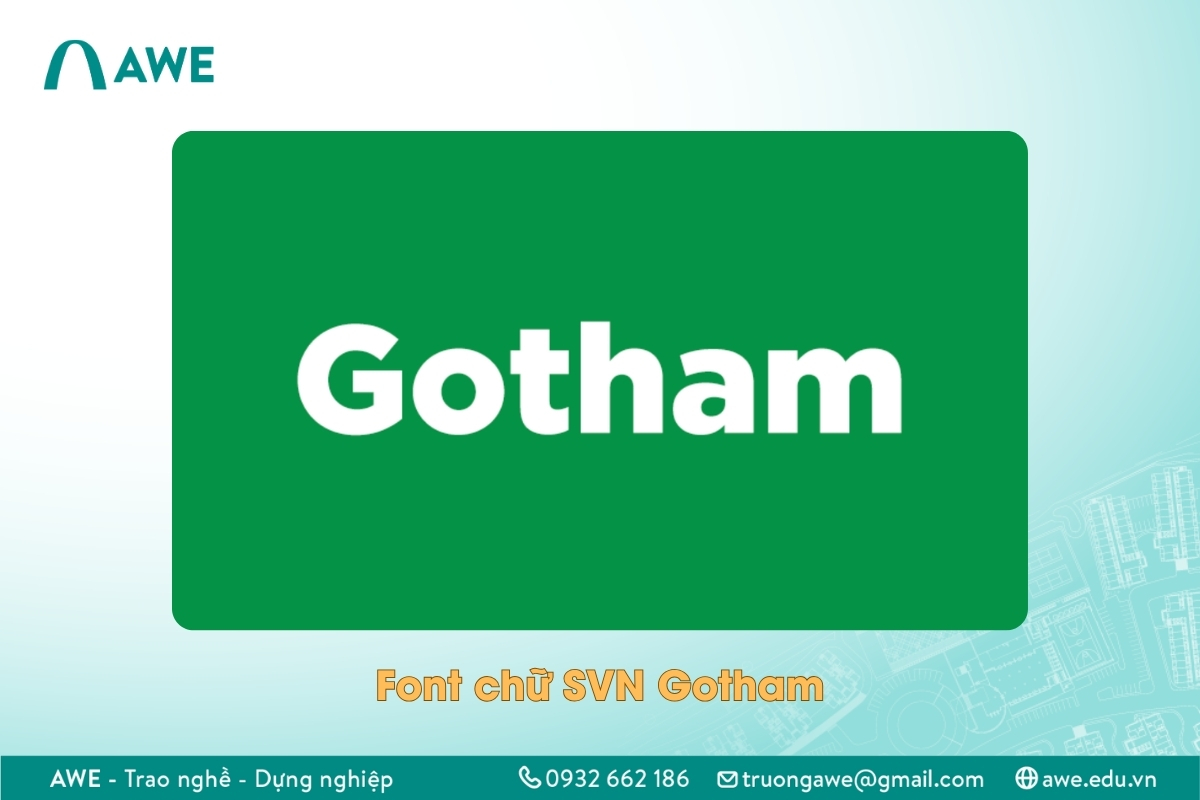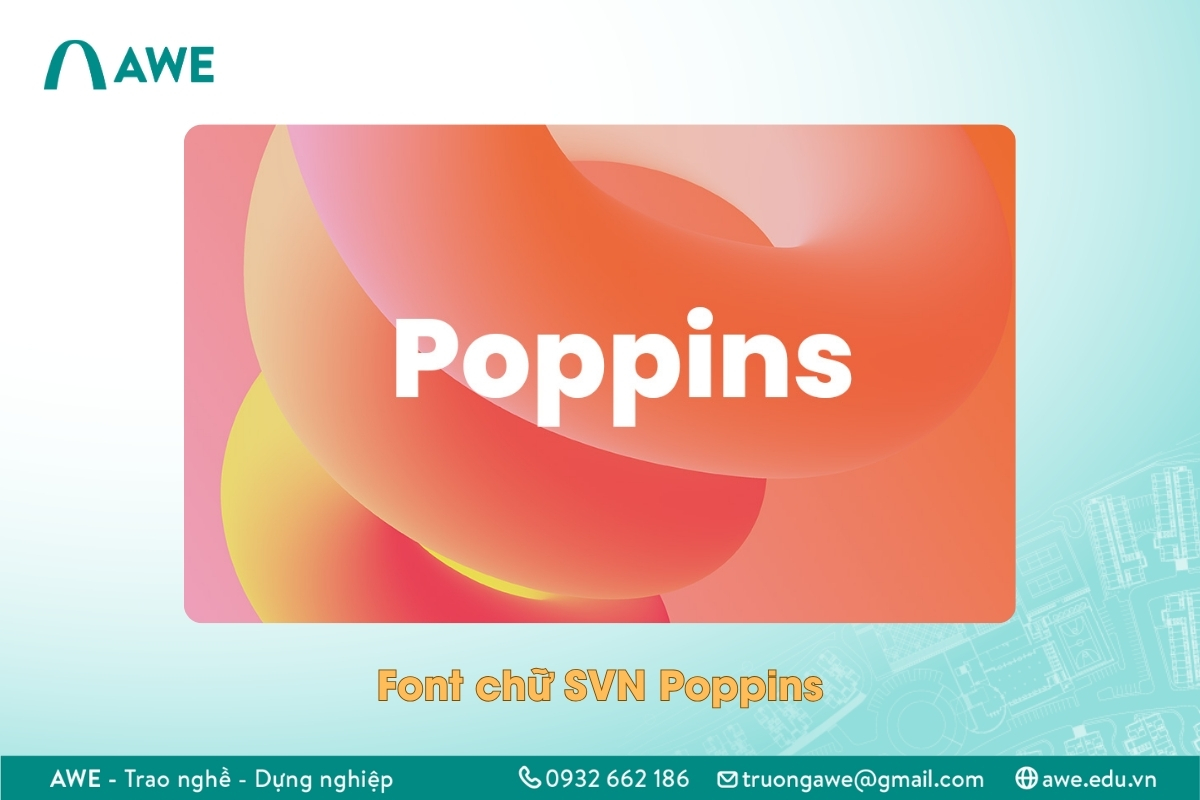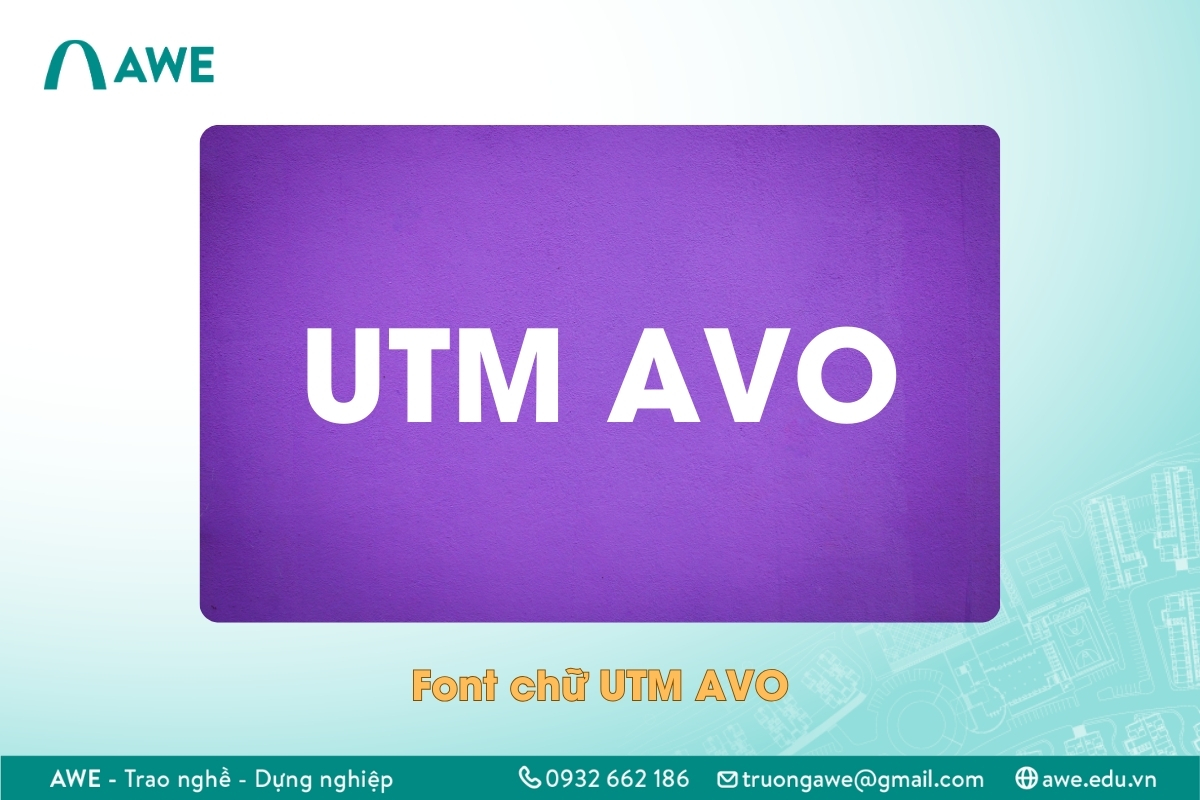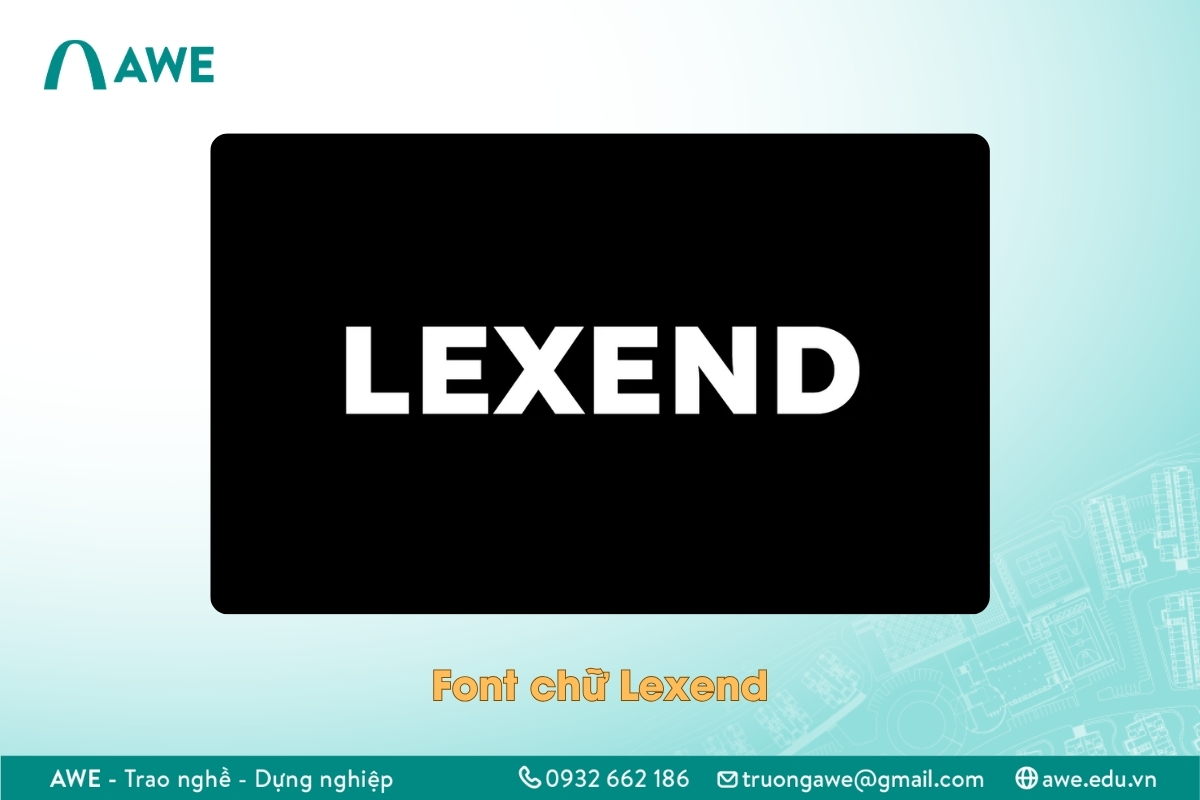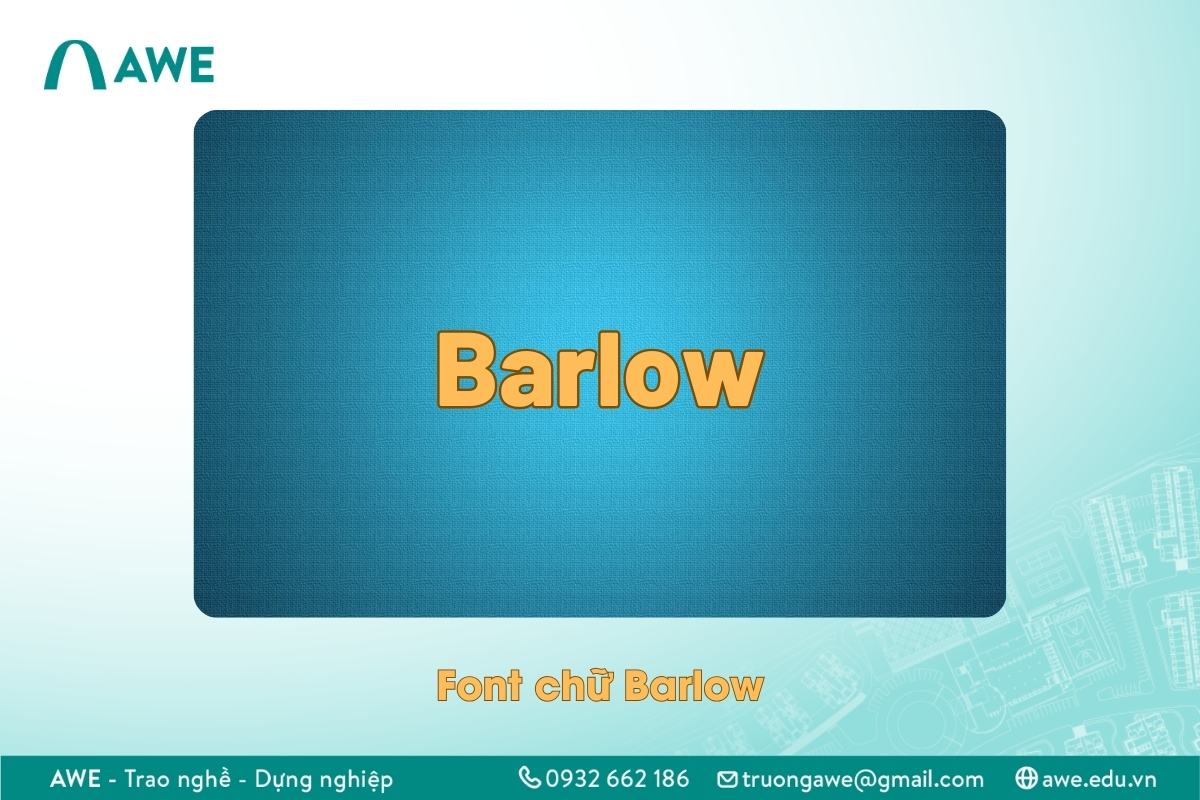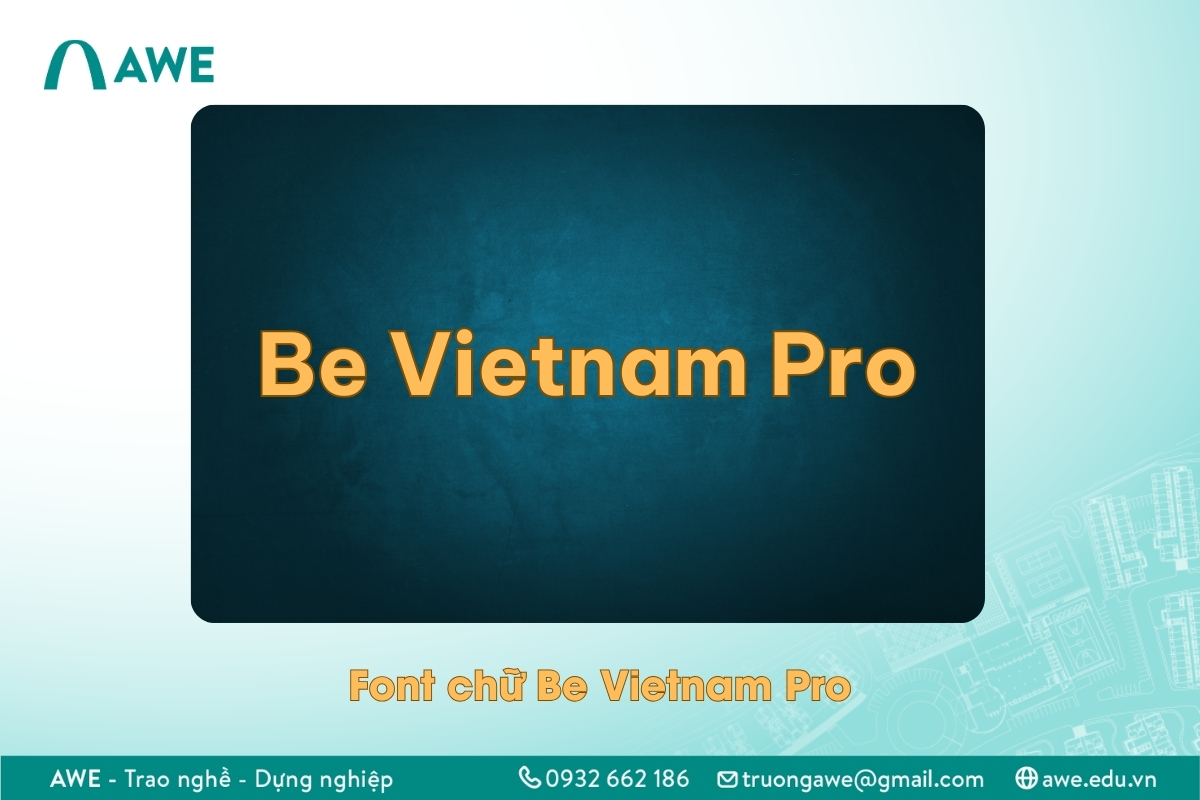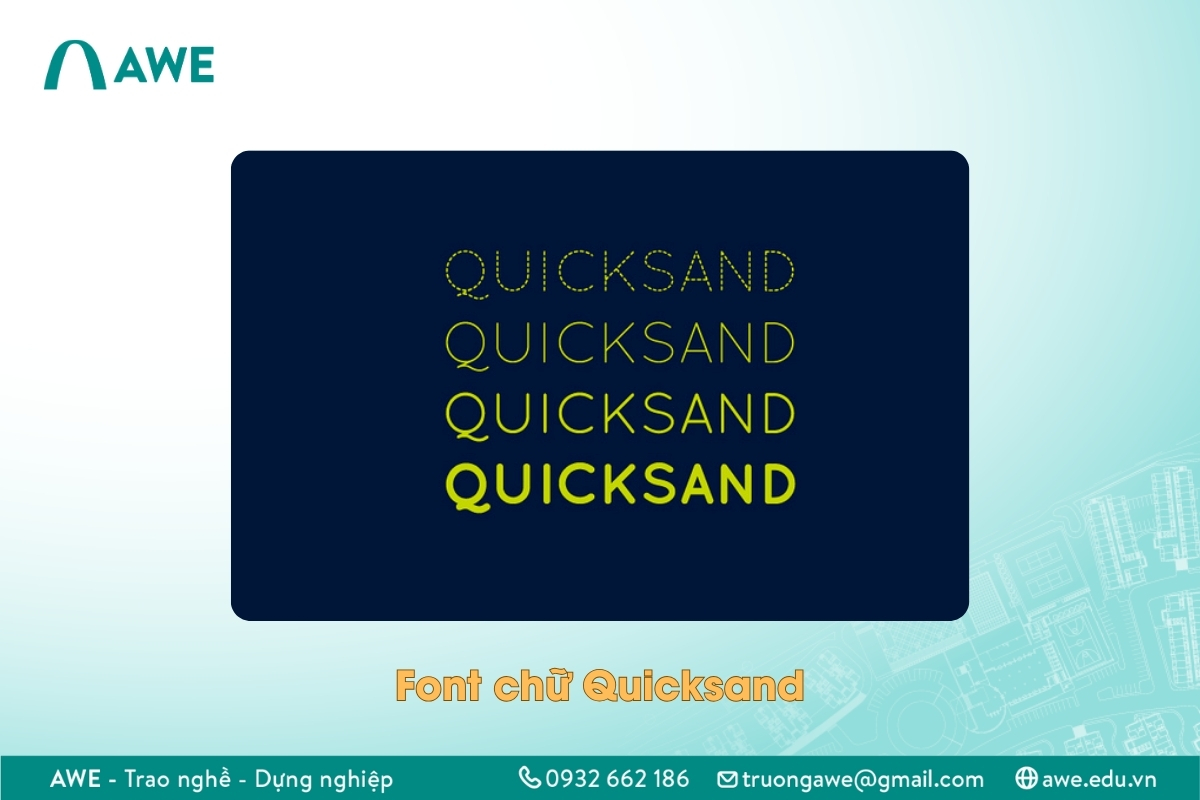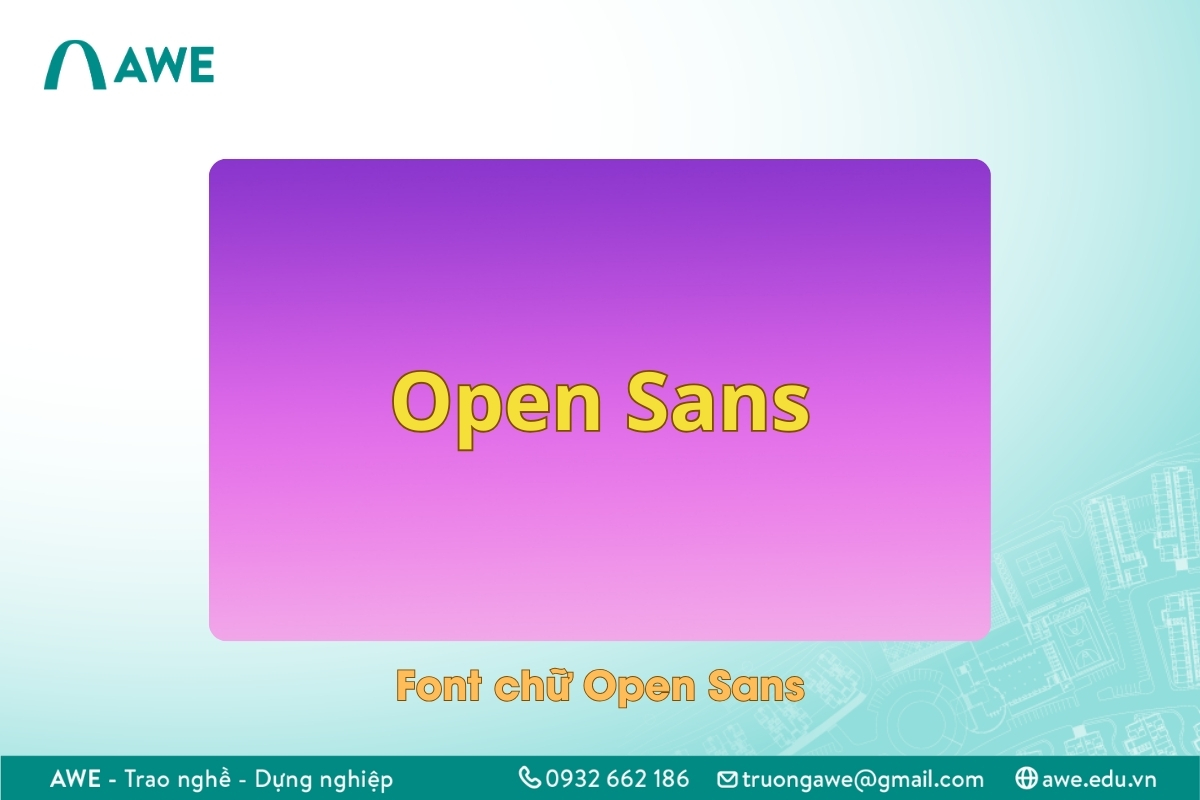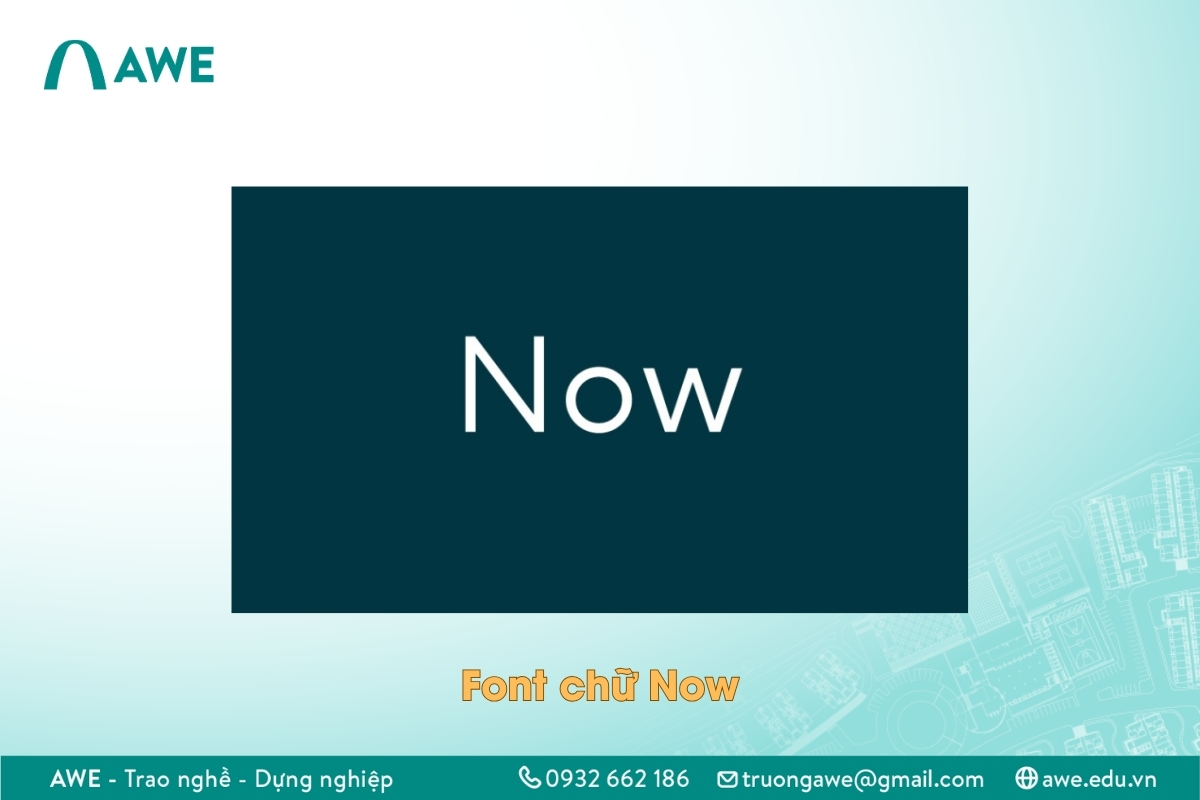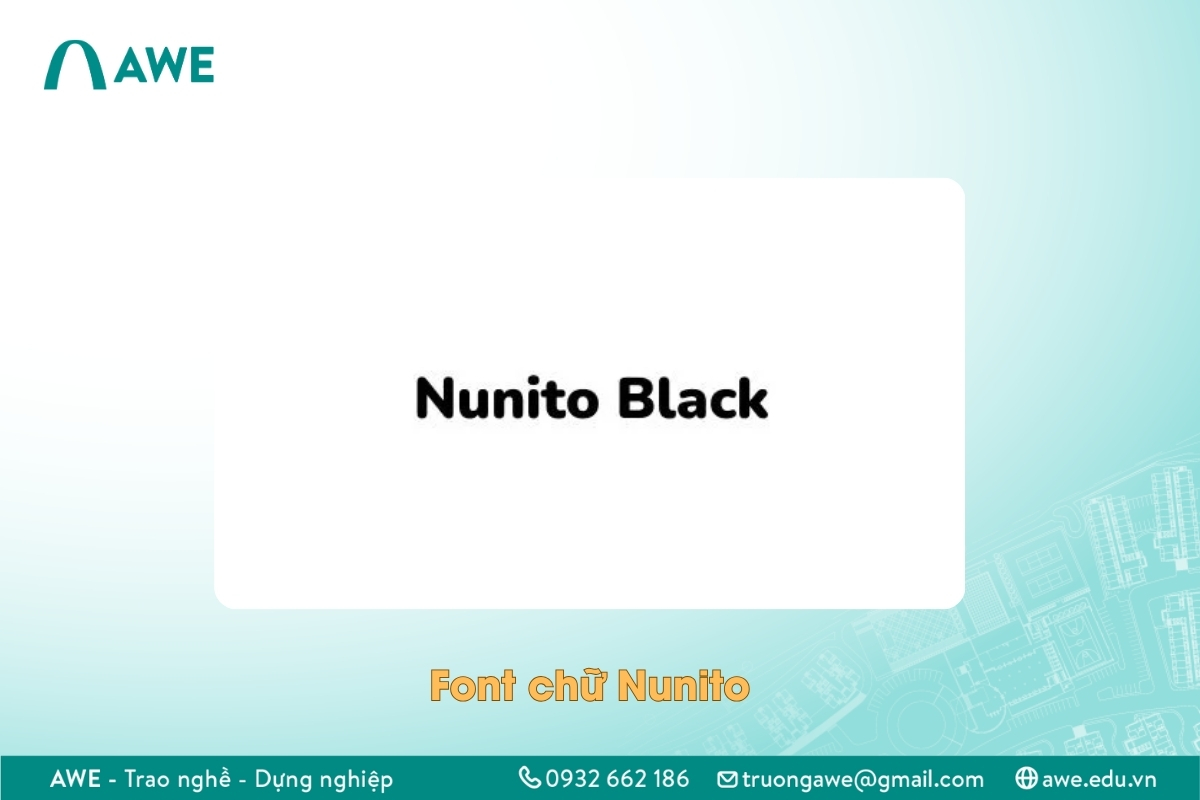
Font chữ không chân (san-serif) là loại phông chữ không có gạch ở đầu hoặc chân chữ. Trái ngược với font chữ có chân, font chữ không chân mang cảm giác hiện đại, tối giản và thân thiện hơn với thị giác người dùng. Bài viết này, AWE sẽ gợi ý cho bạn 15+ font chữ không chân Việt hóa đẹp nhất 2025.
1. TOP 15+ font chữ không chân Việt Hóa chuyên nghiệp
1.1 Font chữ không chân Việt hóa SVN Gotham
SVN Gotham là font chữ không chân được Việt hóa từ bộ font nổi tiếng Gotham của Mỹ. Với thiết kế chắc chắn, hình khối vuông vức nhưng vẫn giữ được khoảng cách cần thiết giữa các ký tự, SVN Gotham mang đến vẻ hiện đại, mạnh mẽ và chuyên nghiệp. Font này cực kỳ thích hợp với thiết kế nhận diện thương hiệu, giao diện web và các chiến dịch truyền thông công nghệ. Gotham chính là font chữ thiết kế logo nền tảng TikTok.
- Font chữ không chân SVN Gotham
1.2 Font chữ không chân Việt hóa SVN Poppins
SVN Poppins có đường nét tròn đầy, đều đặn và mềm mại hơn nhiều so với Gotham. Phông chữ này mang lại cảm giác trẻ trung, thân thiện và có phần “tech” nhiều hơn. SVN Poppins phù hợp cho các dự án thiết kế app, website startup, nền tảng giáo dục, hoặc các thương hiệu nhắm đến thế hệ trẻ. Việc Việt hóa đầy đủ giúp font dễ dàng áp dụng trong nội dung dài lẫn tiêu đề lớn, đồng thời tạo được sự đồng nhất trên đa nền tảng.
- Font chữ không chân hiện đại SVN Poppins
1.3 Font chữ không chân UTM Avo
UTM Avo là một trong những font chữ không chân lâu đời và được ứng dụng rộng rãi trong thiết kế Việt Nam. Font mang kiểu dáng đơn giản, vững vàng với các đường nét sắc sảo, không dư thừa. UTM Avo thường được sử dụng trong thiết kế in ấn như tạp chí, tiêu đề báo, hoặc trình bày văn bản chuyên nghiệp. Font này cũng phù hợp cho các dự án thiết kế mang tính học thuật, kỹ thuật hoặc có yêu cầu về sự rõ ràng và nghiêm túc.
- Font chữ UTM AVO
1.4 Font chữ Lexend Việt Hóa
Lexend được phát triển với mục tiêu cải thiện khả năng đọc hiểu và tốc độ đọc. Cấu trúc các ký tự được thiết kế để giảm độ mỏi mắt, tăng độ nhận diện từng con chữ. Lexend đặc biệt hữu ích trong các thiết kế dạng văn bản dài như sách điện tử, tài liệu học thuật, blog giáo dục hoặc website chia sẻ nội dung chuyên sâu. Với thiết kế thân thiện, Lexend giúp trải nghiệm đọc trở nên nhẹ nhàng, trơn tru.
- Font chữ Lexend
1.5 Font chữ Barlow cho poster, tiêu đề
Barlow là font không chân có hơi hướng hình học nhưng lại rất cân bằng giữa tính hiện đại và khả năng ứng dụng. Lấy cảm hứng từ các bảng hiệu giao thông Mỹ, Barlow có độ dễ đọc cao, kiểu dáng cứng cáp nhưng không khô khan. Font này phù hợp với thiết kế poster, tiêu đề lớn, bảng biểu, hoặc các sản phẩm mang phong cách retro hiện đại. Barlow cũng rất hiệu quả trong việc tạo điểm nhấn trong thiết kế thương hiệu năng động.
- Font chữ không chân Barlow
1.6 Font chữ Việt hóa – Be Vietnam Pro
Be Vietnam Pro là font chữ không chân được phát triển riêng cho tiếng Việt, với khả năng hiển thị tốt cả ở tiêu đề lẫn nội dung dài. Thiết kế thân thiện, linh hoạt, hiện đại và dễ kết hợp khiến font này cực kỳ phù hợp cho UI/UX, thiết kế web, mobile app và các dự án startup. Font mang lại sự chuyên nghiệp nhưng vẫn gần gũi, dễ đọc trong mọi kích cỡ hiển thị.
- Font chữ đẹp Be Vietnam Pro
1.7 Font chữ không chân Việt Hóa Quicksand
Quicksand sở hữu đặc trưng là các đường cong bo tròn nhẹ nhàng, mang đến cảm giác mềm mại, thân thiện và dễ chịu. Đây là lựa chọn hoàn hảo cho các thiết kế mang tính cá nhân, portfolio, blog phong cách sống, thương hiệu handmade hoặc các sản phẩm dành cho nữ giới. Quicksand cũng rất hiệu quả trong thiết kế minimal, truyền tải sự nhẹ nhàng và hiện đại.
- Font chữ hiện đại Quicksand
1.8 Font chữ không chân Open Sans linh hoạt trong thiết kế
Open Sans là một trong những font chữ không chân phổ biến nhất toàn cầu nhờ tính linh hoạt và khả năng đọc tuyệt vời. Với thiết kế trung tính, dễ phối hợp, Open Sans hoạt động hiệu quả trong nhiều ngữ cảnh: từ web, app đến in ấn. Font này đặc biệt phù hợp cho phần nội dung dài, giúp giữ trải nghiệm đọc mượt mà mà không bị mỏi mắt.